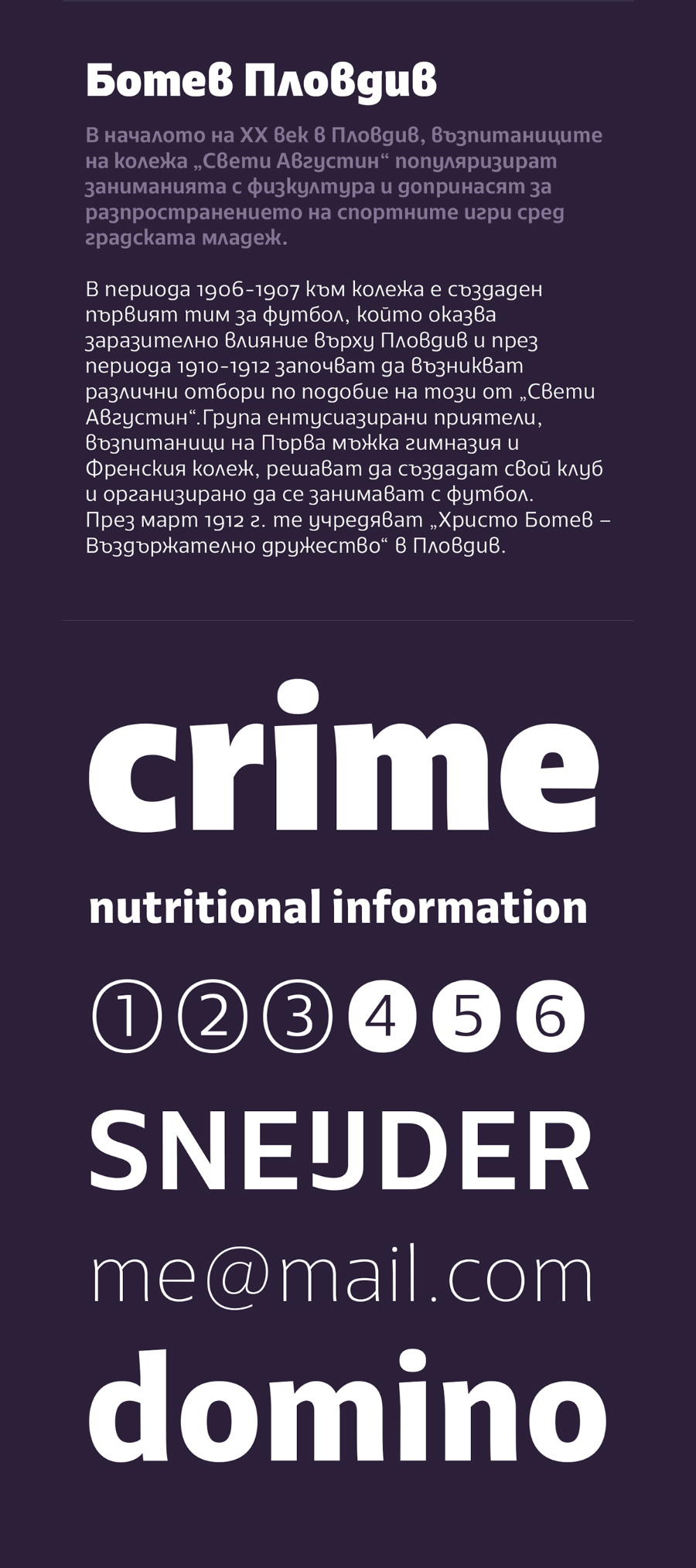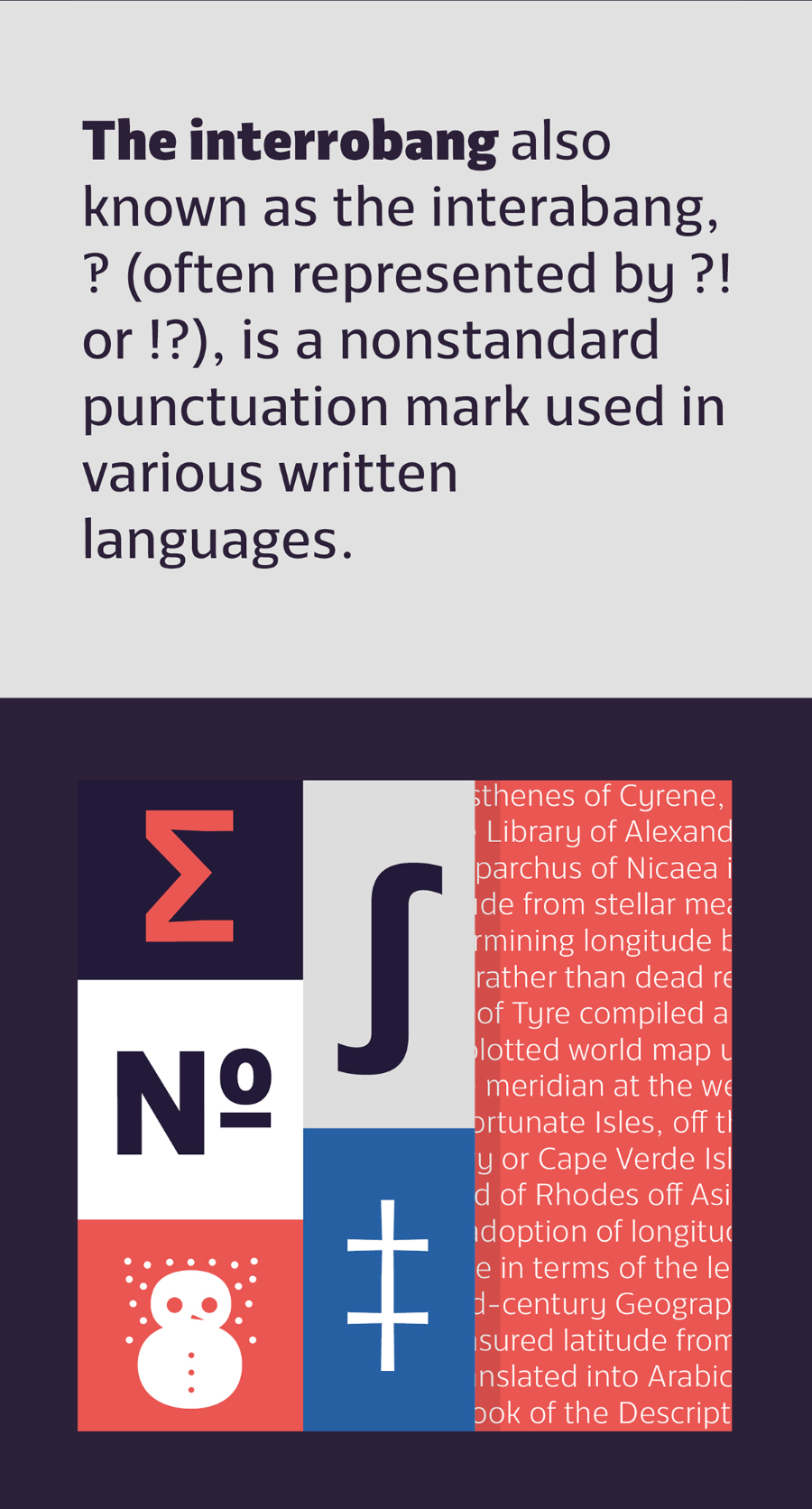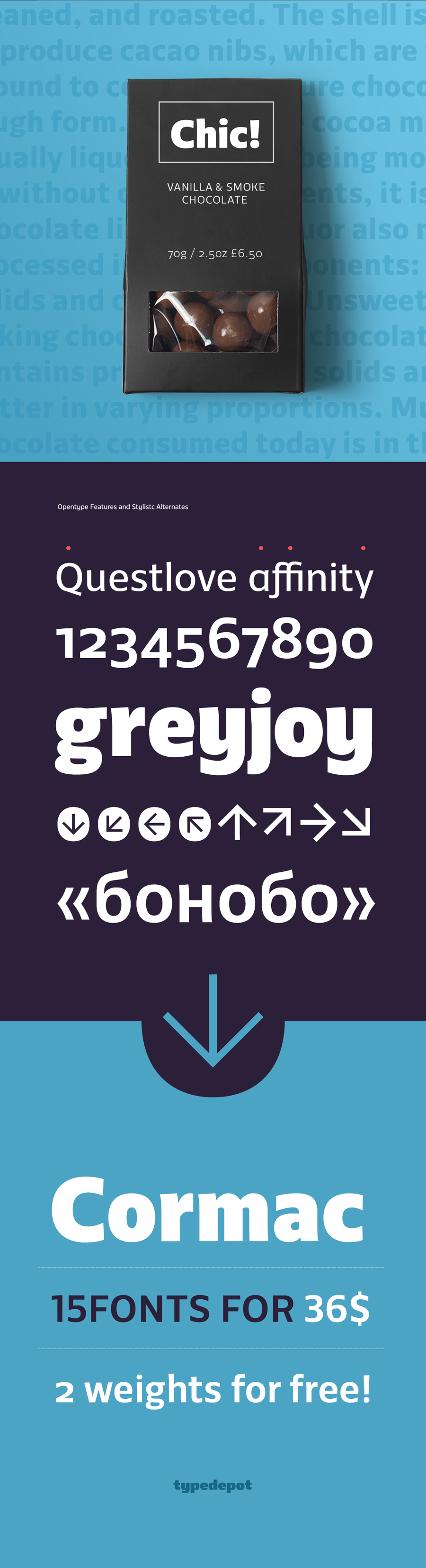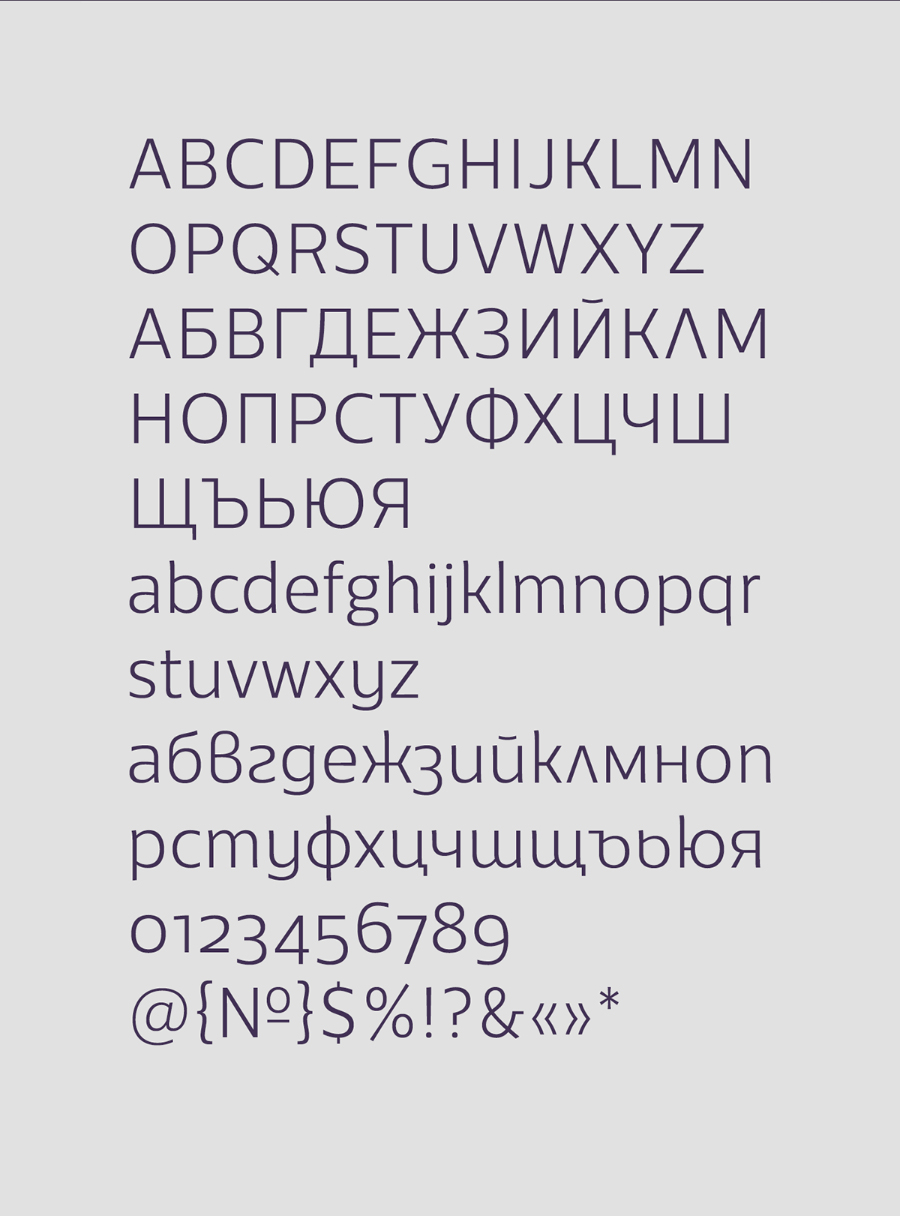
科马克类型家庭免费演示
今天你可以有Cormac Typefamily Free Demo!这次你会得到Cormac Black和Extra-Light。科马克是一个人文主义的字体,其大x高和稍微张开的茎。在项目开始的时候最好的描述这个概念的词是“简单的”。其背后的想法是剥离一切不必要的字母形式,而保持字体有趣。所以,字体很友善,不要太俗气。由于它的人文特色,喇叭上升,并提醒它的书法起源。